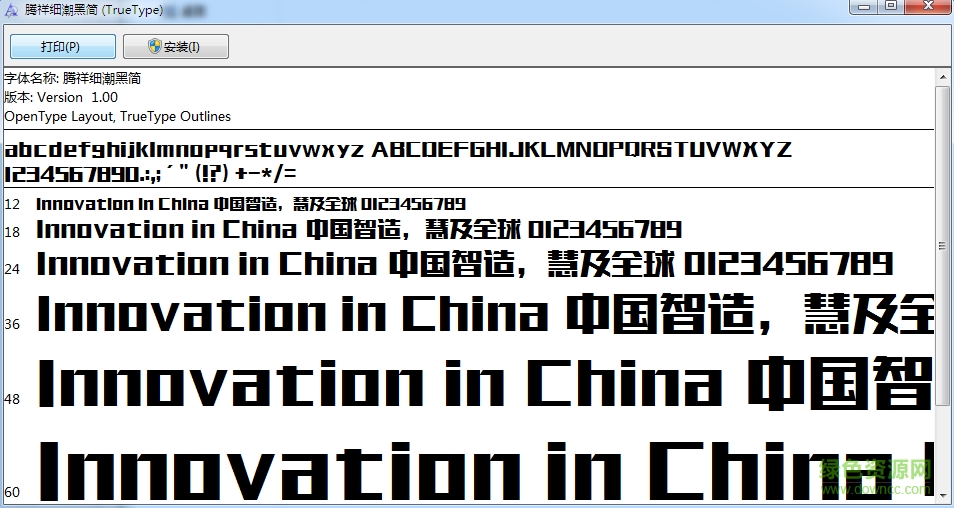
tensentype xichaoheij
tensentype xichaoheij字體是一款筆畫硬朗的美術(shù)黑體字體,結(jié)構(gòu)清晰明朗,線條厚重,字型端莊,十分醒目,一般用作報(bào)刊標(biāo)題或宣傳標(biāo)語,喜歡的朋友快來下載吧!
xiangsif字體特點(diǎn)
細(xì)潮黑筆畫簡潔有力細(xì)微處變換靈動(dòng),即實(shí)用又富有裝飾效果。細(xì)潮黑粗細(xì)適中,比潮黑更清晰易讀。適合標(biāo)題和屏顯用字,可用于印刷出版、包裝設(shè)計(jì)、廣告設(shè)計(jì)、網(wǎng)頁設(shè)計(jì)、屏幕顯示等。